字体心理学:字体选择如何影响您的设计
我们经常谈论营销设计中的象征主义和色彩心理学。 很多时候,品牌的所有决定都集中在这两个主要元素上。
从标志到营销传播,他们利用颜色和符号的力量来传达他们的信息。
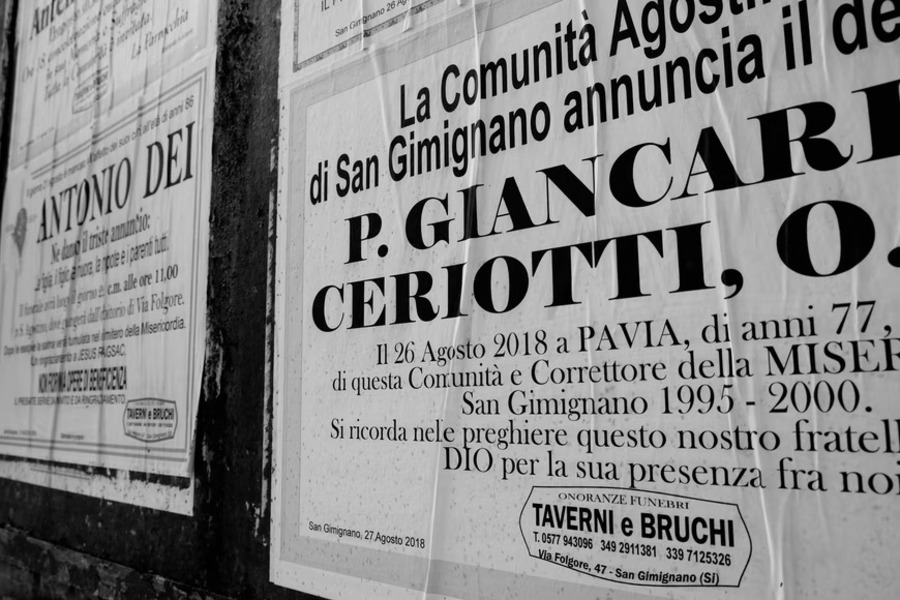
但碰巧的是,即便如此,有时观众也无法掌握正确的信息。 这给所有相关人员带来了极大的失望和困惑。 如果你真的仔细研究这个问题,答案并不难。
是的,除了颜色和符号,营销设计也需要使用正确的字体和字体。 如果您直到现在还没有意识到,我们正在谈论字体和字体心理学原理对您的设计的影响。
虽然与色彩心理学相比,字体心理学是一个相对未知的概念,但它同样重要,甚至更重要。
您选择的字体会对您的受众、他们对品牌个性的理解、信息传递等产生重大影响。 它甚至会影响他们对特定产品或服务的感觉。 或者你的品牌作为一个整体。
现在你知道为什么人们会对字体如此着迷以至于他们会在网上争论它们。 字体可以带来很多情感!
如果这一切听起来有点多,请不要担心。 因为本指南旨在为您分解字体心理学。 在 Kimp 的这篇博客中,我们将处理字体心理学中的主要概念,并确保您可以为您的设计选择最好的字体。
所以事不宜迟,让我们开始吧。
字体心理学:为什么你的设计需要它
字体心理学是营销神话吗? 你的设计中真的需要它吗? 正如大家所说的那样,它能产生很大的影响吗?
好吧,在我们回答这个问题之前,我们想问你几个问题:
当有人用大写字母输入信息时,您是否讨厌它,因为感觉他们在大喊大叫? 华丽的、弯曲的和不匹配的字体让你有什么感觉? 你有最喜欢的字体类型,如果有,为什么?
如果您对这些问题的回答涉及某种情绪反应,那么您就知道字体可以在很大程度上塑造您的看法。
作为营销人员或品牌经理,您希望客户以您想要的语气 100% 地接受您的信息。 一个小失误或误解可能会非常昂贵。
Mehrabian 的私人交流规则指出,93% 的私人交流是非语言的。 这取决于您选择的媒介和设计风格,而不是文字。
因此,当您花费数小时为您的营销活动选择合适的词时,是时候注意您如何说这些词了。 是的,语气很大程度上取决于选择正确的字体。
Kolenda Font Mannequin 理论还告诉我们,当人们与各种字体交互时,他们会剖析它们的属性,最终将这些属性与他们正在阅读的品牌或信息联系起来。
这意味着最重要的是,为了品牌一致性,您必须在所有通信中使用相同的设计元素,例如颜色、图像和字体。 了解它如何让客户感受到会对您的成功产生巨大影响。
字体心理学:为您的品牌选择合适的字体
我们已经讨论了很多关于为什么你现在需要为你的品牌跳上字体心理学的问题。 但我们不能止步于此,不是吗? 不,我们还必须了解每种字体与其最终适用的品牌之间的关系。
不过,在我们详细探讨字体心理学的概念之前,请注意。 许多这些概念是基于专家如何看待一般观众的看法。 但这些可能非常笼统,为了获得最佳结果,我们建议您在开始之前对目标受众进行彻底的研究。
一个小例子是关于字体心理学的流行文章声称有些字体是男性的,有些是女性的。
在一个不断发展的世界中,这种解释可能对更进步的观众根本不起作用,但可能适合保守的观众。 这一切都取决于您的目标受众以及您想用您的品牌吸引谁。
我们在下面给出的框架就是——一个框架。 如果您希望设计中的字体像 T 恤一样适合您的品牌,那么除了阅读此博客之外,您还有一个额外的步骤。
现在让我们来看看一些流行的字体及其通常相关的特征。
流行字体及其特征
在我们之前关于为您的品牌选择正确字体的博客中,我们介绍了在此过程中必须记住的各种因素。
其中之一是一些流行字体的感知特征,以便品牌可以选择他们认为最能代表他们的字体。 我们在这里转达一个快速快照供您参考。 这些特征和我们在后面章节中介绍的因素将让您全面了解字体心理学及其工作原理。
主要是,除非品牌使用自定义字体样式,否则您随处可见四种流行的字体样式。 他们是:
- Serif 字体:传统上用于印刷媒体的字体,客户经常将 Serif 与稳定性、专业性、传统和可敬性等价值观联系起来,仅举几例。
- Sans Serif 字体:网页设计字体或 Sans-Serif 是 Z 世代的最爱。他们认为它时尚、现代、优雅、别致和年轻。
- Script fonts :这种字体代表一种手写和书法的书写方式。 绝对比前两款更文艺,代表了一个俏皮、年轻、摩登、酷炫的品牌个性。
- 显示字体:通常是流行字体类型的定制和创新版本,显示字体代表了一种古怪、非传统和开创性的个性。
您在营销界看到的任何其他字体样式都将结合这些类别。 由于自定义字体是 2022 年的主要趋势预测,我们预计会有许多新的字体样式出现。
既然我们知道了字体在情感上广泛代表什么,让我们再深入一点,探索字体心理学在不同设计中的应用。
跨设计类型的字体(根据字体心理学)
我们觉得颜色比字体更容易导航。 为什么? 因为有三种原色和有限数量的流行色,所以为一个品牌挑选一种或一组颜色变得很容易。 您可以根据需要对其进行更改,但基础工作非常可行。
字体是完全不同的球赛。 只需改变字体的粗细或样式,就可以改变消息的整体含义。
更不用说,虽然品牌可以尝试为品牌选择一种单一的字体样式,但营销信息每次都必须根据上下文和目标受众进行钓鱼。
因此,我们不会告诉您每种字体的含义(这是一个非常详尽的列表),而是向您展示如何在营销设计中利用心理学原理。
我们为什么这样做呢? 因为正如我们所说,我们预计自定义字体将在 2022 年引领潮流。
字体心理学和品牌
那么,你想设计你的品牌吗? 这包括诸如徽标、品牌名称和您拥有的任何标语之类的内容。 考虑到视觉效果如何比文本更有效地传达给客户,这是一个好主意。 视觉效果也具有很高的回忆价值。 但是现在你被困在选择哪种字体或者更确切地说你的品牌的字体应该是什么样子的问题上? 这是一个非常重要的决定,因为它如何成为您视觉识别的内在部分。
任何字体要成为您品牌的字体都有一些先决条件:
- 它必须适用于数字和印刷媒体。 您可以选择适合网络的字体,因为现在您只有一个应用程序,但是当您需要离线做广告时,这会带来很多麻烦。
- 字体样式的主要特征必须与您的品牌个性相匹配。 是的,营销实验的空间很大,但基本特征至少必须匹配。 客户通常会寻找非常简单的东西,您不想错过这个优势。
- 字体必须以某种形式在视觉上代表您品牌的个性。 它可以通过象征、颜色或整体设计来实现——但它必须,特别是,因为你在品牌设计中使用它。
Kimp 提示:当客户与您的设计互动时,他们会同时吸收所有元素——颜色、形状、尺寸、风格和象征意义。 因此,重要的是您还要选择一个整体有效的设计,而不是过度关注元素。
如您所见,这两个徽标散发出完全不同的氛围,它们之间的主要区别在于我们的团队为它们选择的字体。
字体心理学和品牌传播
好的,我们都知道客户非常重视品牌传播。 他们阅读、剖析并把它们放到互联网上让全世界看到。 因此,做好这件事变得至关重要。
设计、布局和颜色会对您有所帮助,但往往是字体选择才能达成交易。 当客户看到您的标题时,它在某种程度上为他们如何看待信息的其余部分定下了基调。 从第一个字母开始正确,就像 Netflix 对其系列和电影标题所做的那样。
“黑镜”的字体完全不同,表明这是一场情感表演,而“王冠”的字体则表明这是一场关于旧价值观的表演。
官方通信可以使用衬线字体权威而直接,也可以使用脚本字体有趣而古怪。 这完全取决于您要传达的信息。
字体心理学与营销
品牌化后,您在哪里使用字体? 营销设计,对吧? 所以不用说,你在这里选择的字体也必须来自字体心理学。 通常,营销从心理学领域大量借鉴,以便您可以有效地影响您的客户。
字体是这条道路上自然而然的下一步。
营销变得越来越视觉化,而且这种趋势将持续存在。 尤其是在数字营销中,客户的注意力一直处于历史最低点,而设计是吸引他们眼球的唯一工具。 在观众看到您的内容的瞬间,设计确保它传达正确的情感,以便他们留下来。
这包括三个主要部分:
基于目标受众
正如我们在介绍部分所说,字体心理学原理借鉴并建立在观众对各种字体的反应之上。 随着世界的变化,这些看法也会发生变化。 您的字体选择也必须相应更改。
例如,如果您要向保守的老年男性和老一代推销保健产品,那么您的字体首先必须散发出阳刚之气和力量。 除了健康之外,您还希望字体能够传达大胆、冒险和热情等特征。
但是,如果你向更年轻、更细致的一代推销同样的产品,你可以选择表现出弱点和力量,并选择更柔和的字体样式。
了解了解您的目标受众有什么不同?
基于品牌个性和行业
这是一个典型的建议,我们在前面关于品牌设计的部分中已经介绍过。 但碰巧你不能在所有场合都使用相同的品牌字体。 有些在视频、动画等方面效果不佳。 或者您希望传达的产品/信息需要一些额外的东西。
在这种情况下,我们建议选择反映以下内容的辅助通信字体:
- 品牌个性
- 行业标准
- 重要的品牌特征
基于情绪
这是我们最喜欢的部分。 因为它可以让你真正了解字体心理学的神奇之处。 最重要的是,了解本节将有助于设想您的自定义字体的外观。
您可以根据您希望客户的感受自定义字体。
例如,对于快乐的消息,您可以选择脚本字体作为基础并在其上进行构建,使其对您的消息来说是独一无二的。 根据您的品牌风格指南,使用您选择的颜色、风格和设计风格对其进行自定义。 带有曲线和循环的脚本字体让每个人都感到快乐,将是传达兴奋、幸福和快乐的完美选择。
同样,您是否注意到耐克在其所有动机海报和营销活动中使用的字体? 他们使用一系列字体,但都属于无衬线字体家族,通常用粗体表示权力的感觉。 他们的图像和强大的强硬字体的综合影响使其成为杀手组合。
但它只是为了快乐和感觉良好的情绪吗?
不。在他们的一个忧郁的信息中,ASPCA 选择了一种简约而简单的无衬线字体,真正把重点放在了家里。
为您的设计选择有影响力的字体
我们发现清单非常有帮助,我们希望您也这样做。 在介绍了字体心理学的基础知识以及如何在各种设计中利用它之后,这里有一个选择最佳字体的快速清单。
- 您要选择的字体的主要特征是什么?
- 它是否符合您的品牌个性?
- 客户通常会与此字体相关联吗? 当你选择这个来代表你的品牌时,这对你有好处吗?
- 字体是否与其他设计元素配合得很好?
- 如果它是一种营销字体,它是否与您选择的品牌字体搭配得很好?
回答这些问题将使您更接近基于字体心理学为您的设计选择正确的字体。
今天我们学到了很多关于字体的知识。 谁知道选择字体会如此复杂? 好吧,我们现在知道字体选择可以完全成就或破坏您的设计。
因此,在不了解隐藏信息或其对品牌成功的影响的情况下,无需再延迟或选择通用字体。